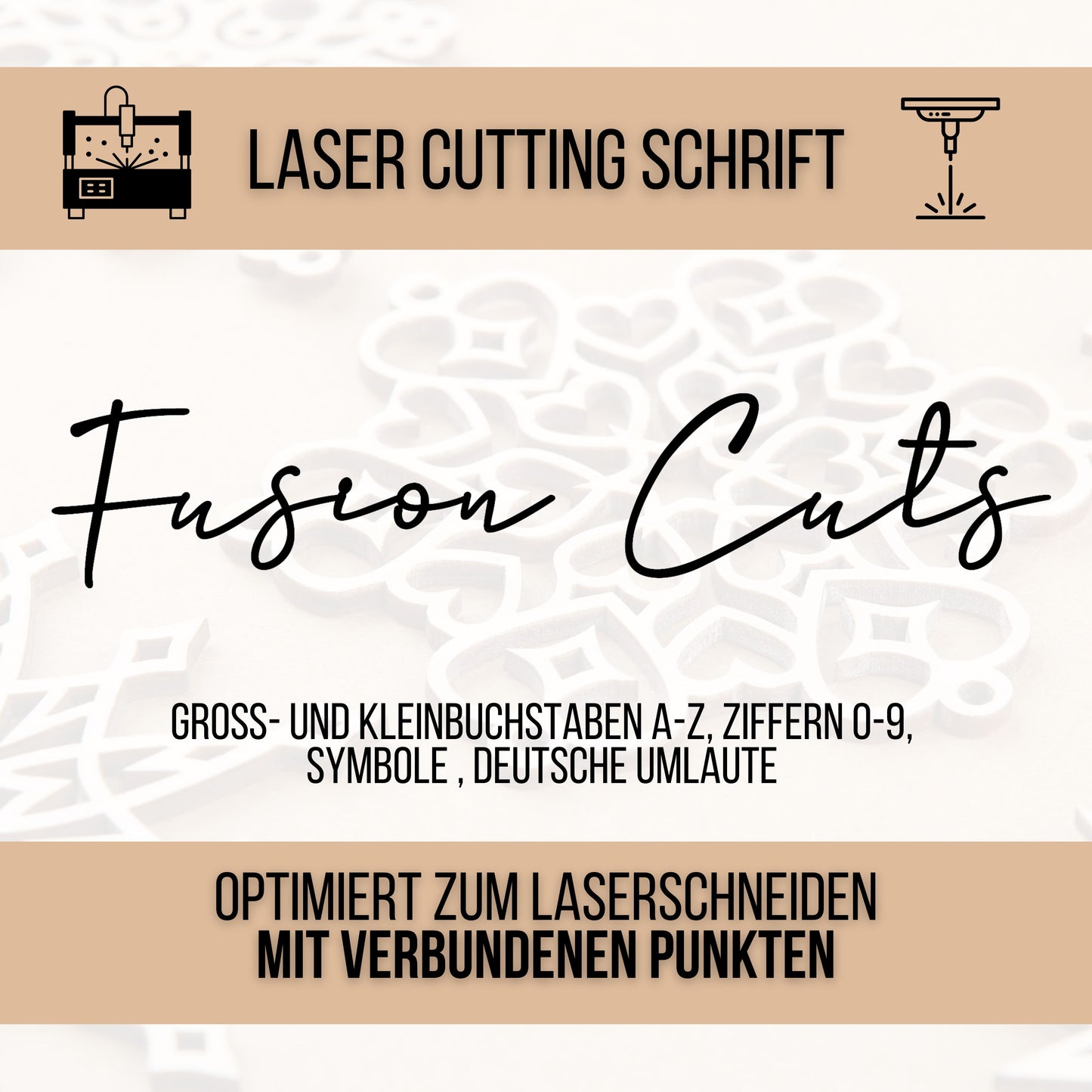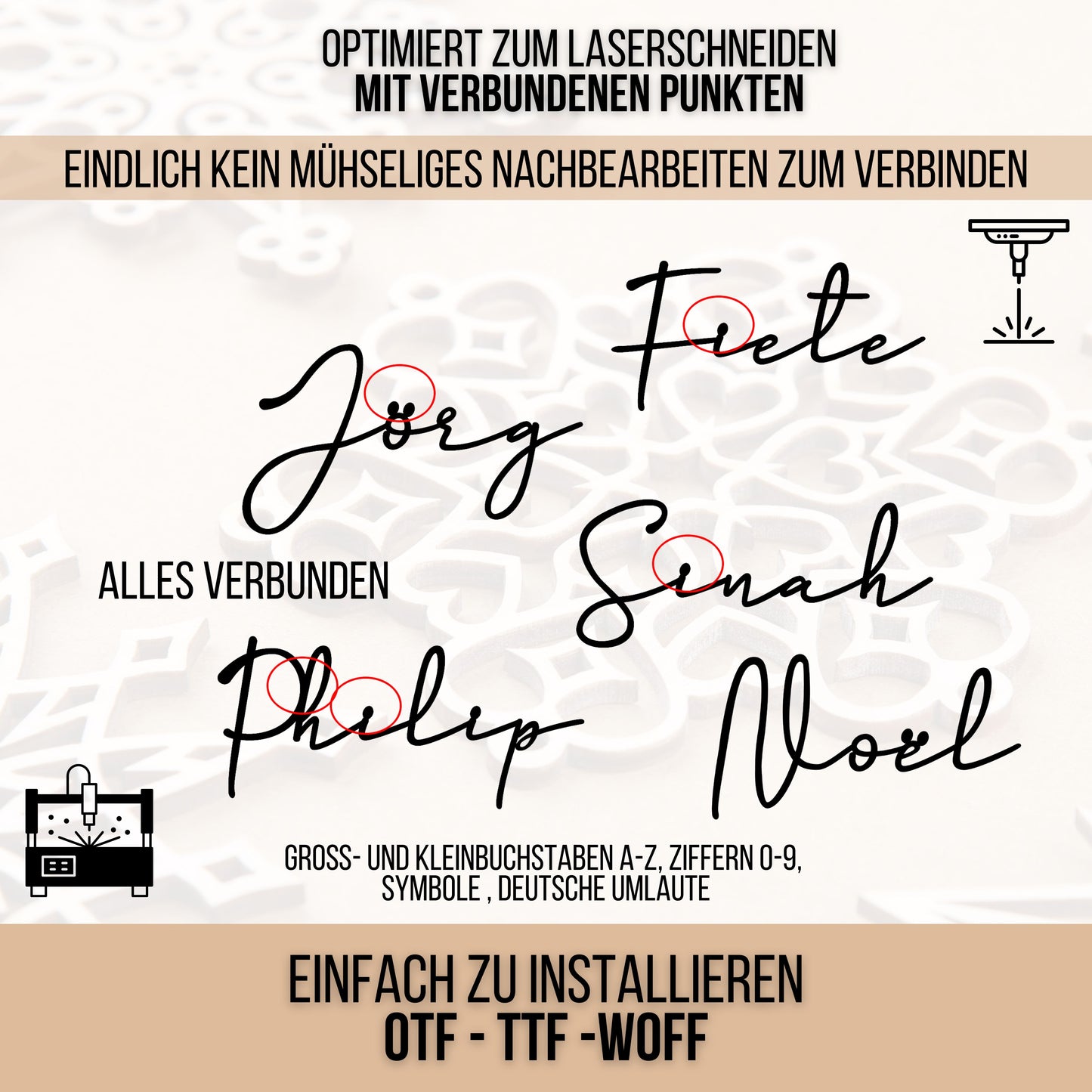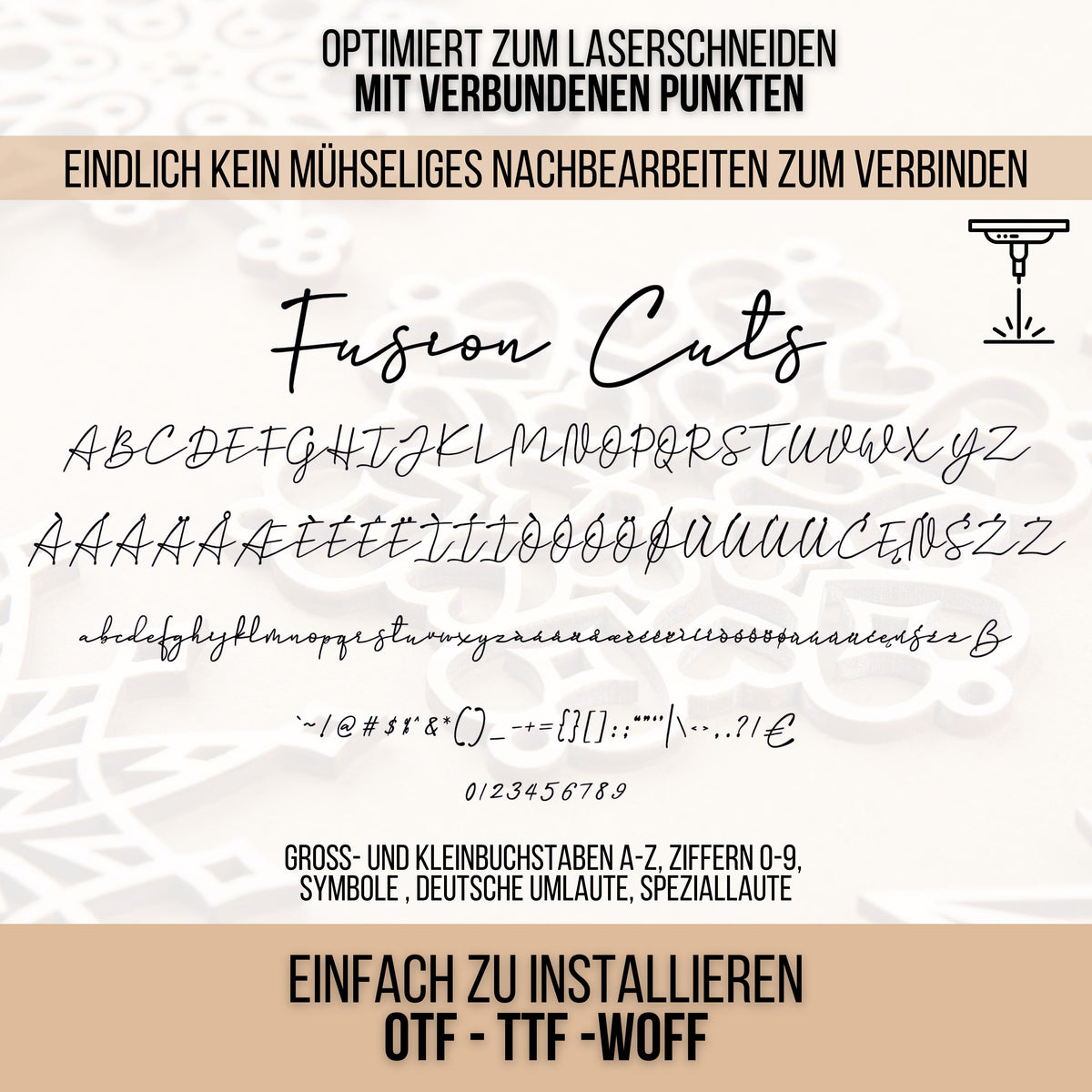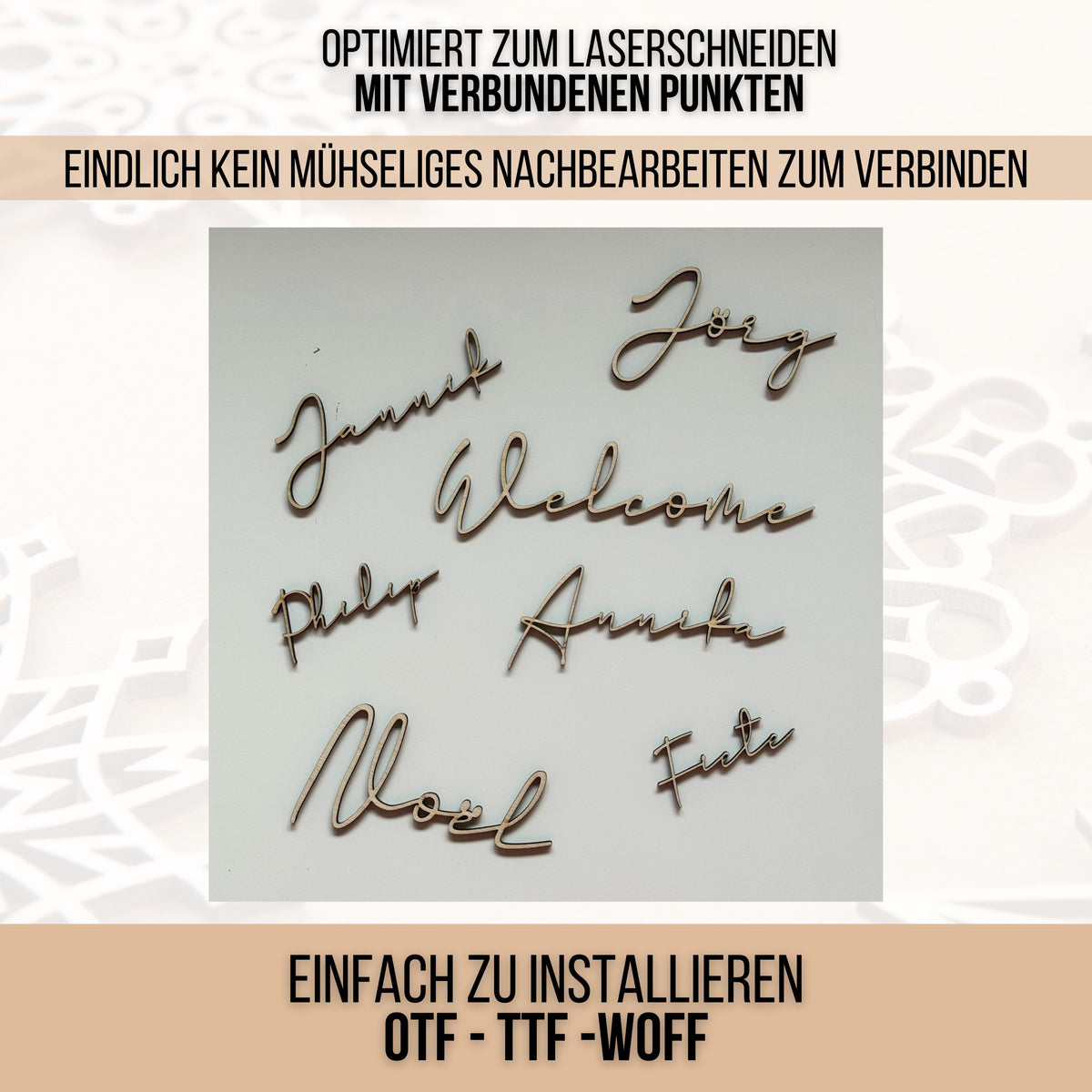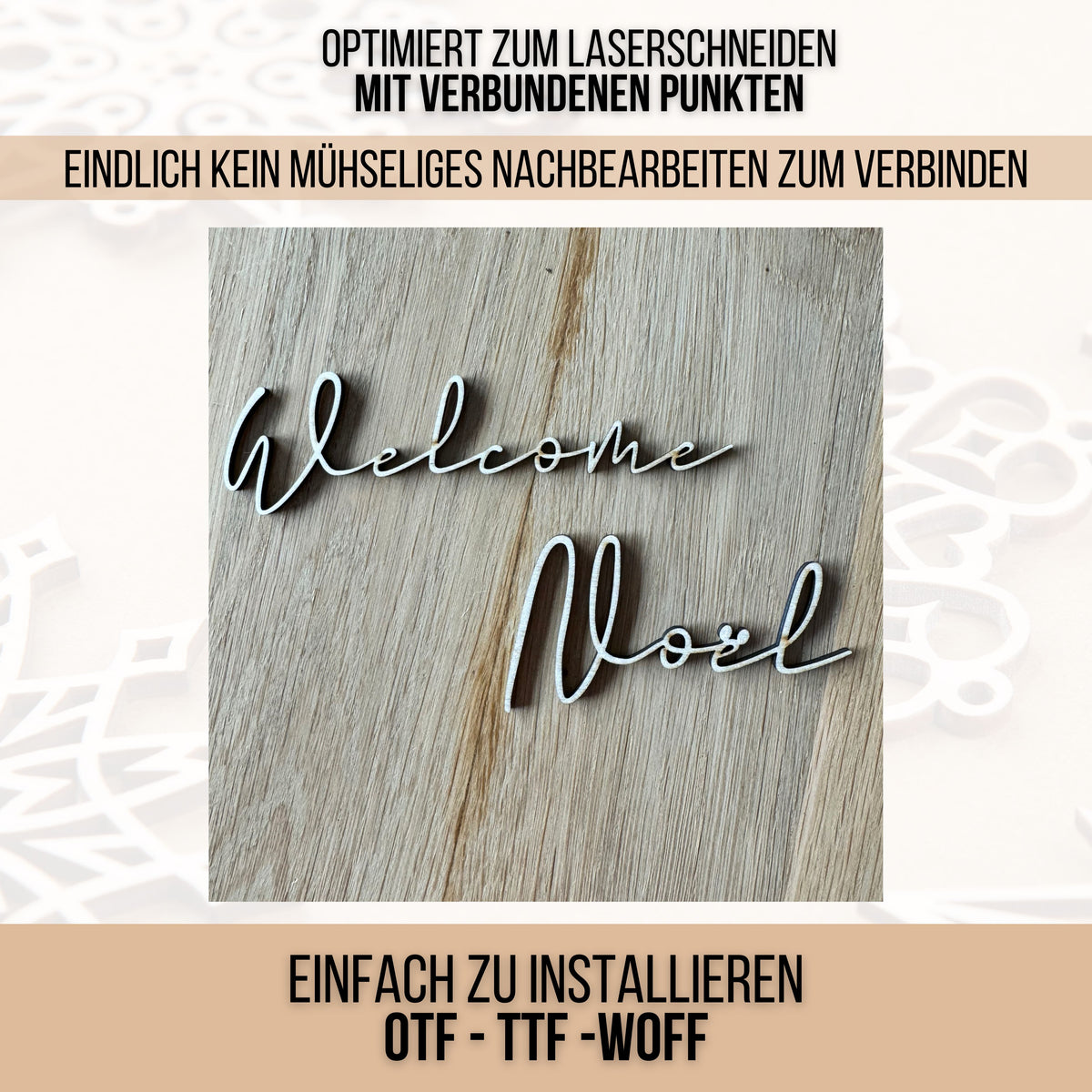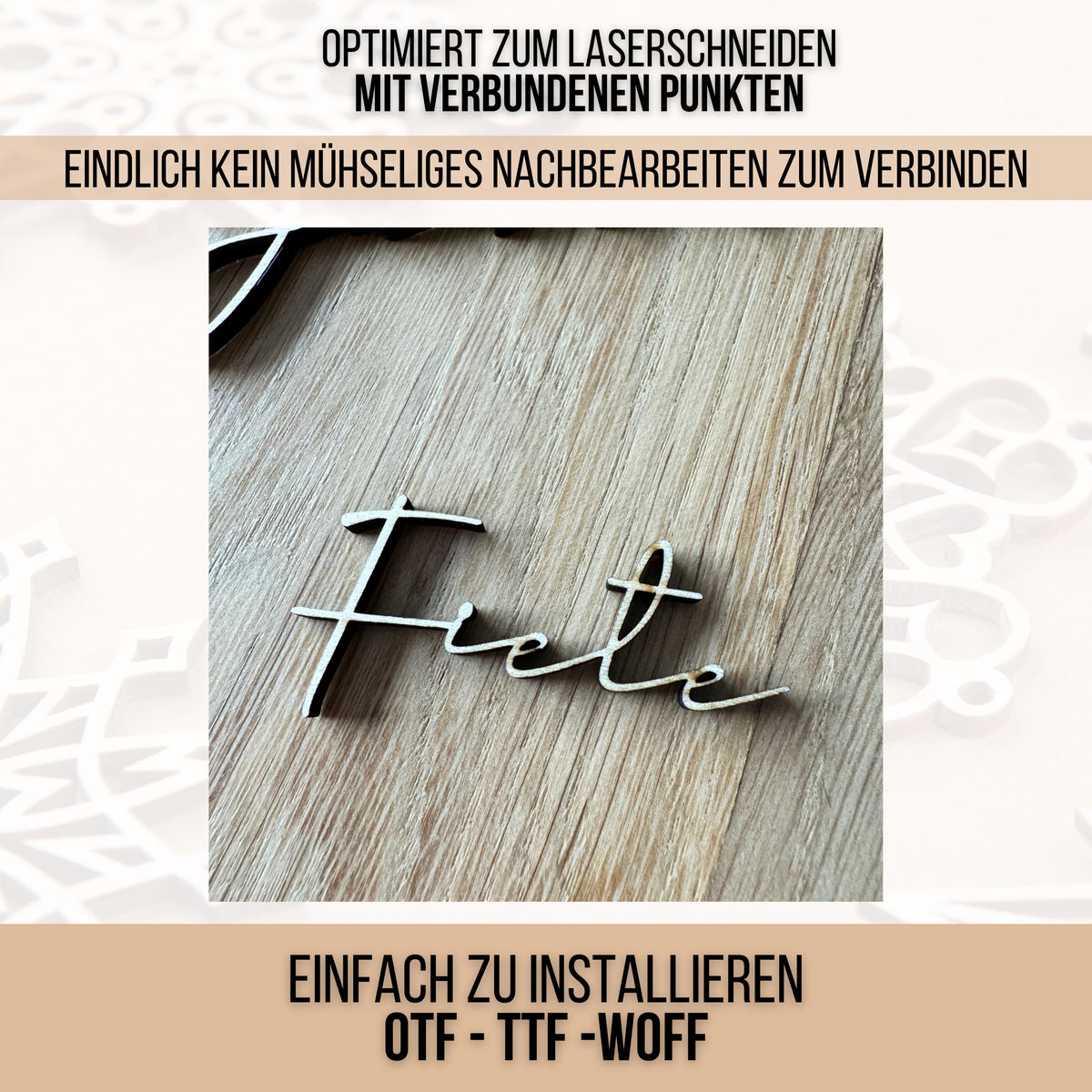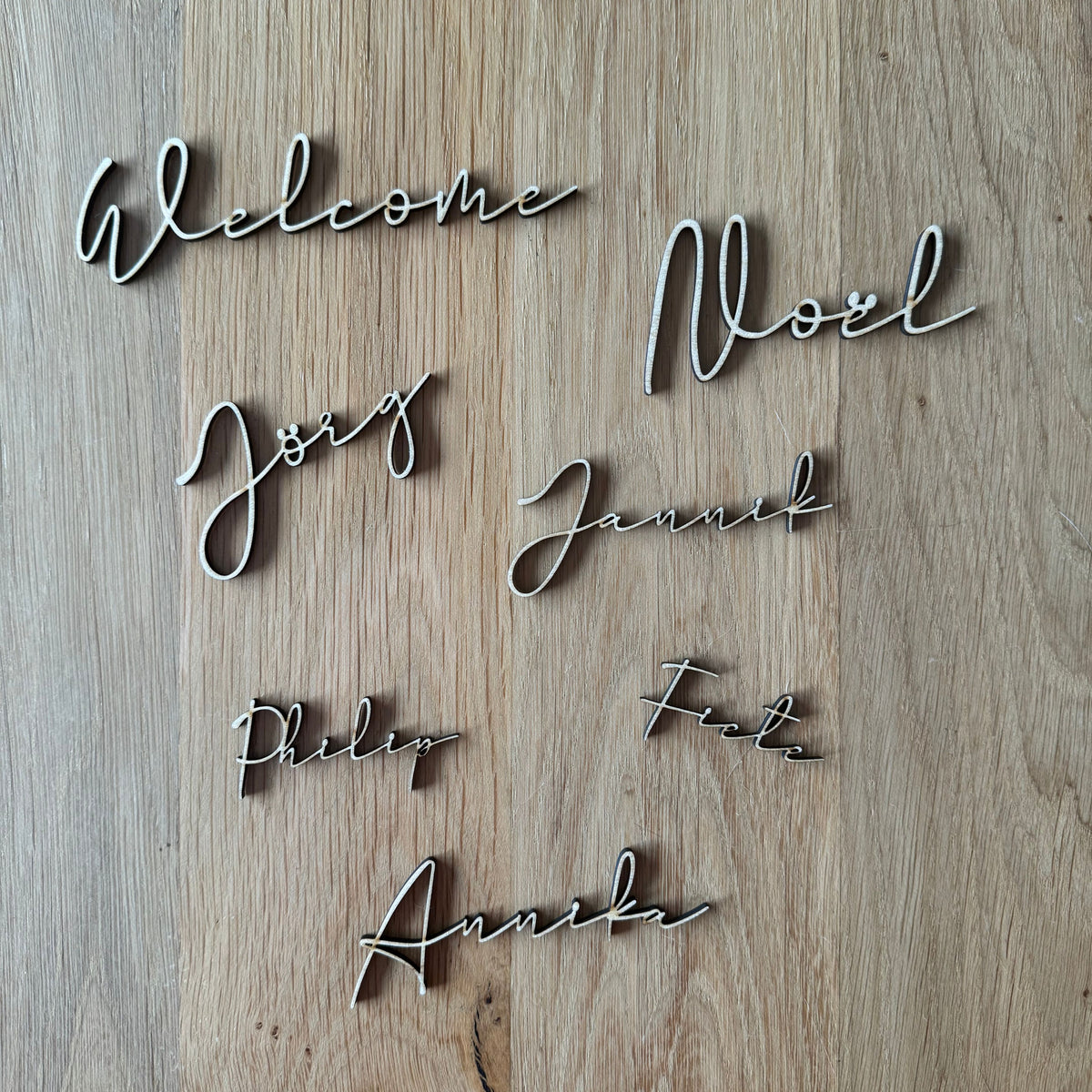
Fusion Cuts – Schriftart für Laser, Plotter & 3D-Druck
Laserschrift ohne Nachbearbeitung – direkt schneidefertig
Kennst du das Problem? Buchstaben ausschneiden, Punkte auf i, j oder Umlauten fallen raus – und du sitzt danach ewig dran, alles manuell zu verbinden.
Diese Schrift löst genau das.
Alle Buchstaben und Punkte sind bereits miteinander verbunden – du lädst die Datei runter, schickst sie direkt an deinen Laser, Plotter oder 3D-Drucker, fertig.
- Alle Buchstaben verbunden – keine Nachbearbeitung nötig
- Umlaute & Sonderzeichen enthalten